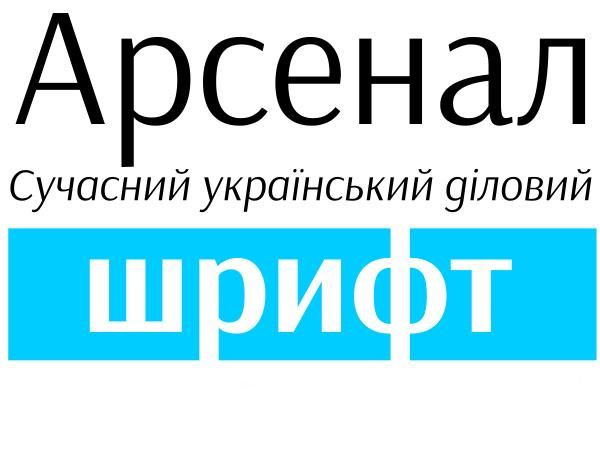
Шрифт АРСЕНАЛ / type.org.ua
На общенациональном открытом конкурсе "Украинский шрифт" победил шрифт АРСЕНАЛ. Уже сейчас он вошел в использование.
Первыми его начали использовать сами организаторы конкурса. Они ведут новым шрифтом свои сайты.
Организаторы призывают всех использовать украинский шрифт в делопроизводстве и повседневной жизни.